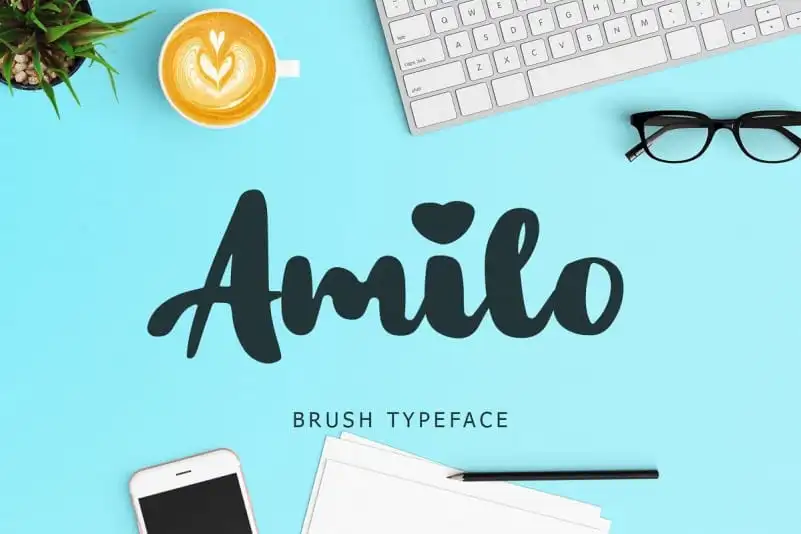
Aqui está uma descrição para a página de download da fonte ‘Amilo Bold Script Font’, adaptada aos requisitos solicitados: Amilo Bold Script é uma tipografia de script bold que transmite uma sensação forte e limpa, ideal para criar um design com personalidade. Esta fonte foi criada por Lyth Creative e incorpora o estilo clássico da escrita com um toque mais moderno. Seja em um layout editorial ou em um projeto de identidade visual corporativa, Amilo Bold Script oferece uma maneira elegante e distintiva para destacar seu trabalho. Seu design limpo e forte lhe dará a chance de criar algo que seja tanto estiloso quanto funcional, proporcionando uma impressionante aparência ao seu design final. Nesse blog de recursos gráficos, desejamos ajudá-lo a encontrar a fonte perfeita para complementar suas criações. Se você está procurando por uma fonte script bold que dê um toque elegante e moderno aos seus projetos, Amilo Bold Script é definitivamente uma escolha inteligente. Esperamos que esta descricão seja útil para você em sua busca de recursos gráficos excelentes!